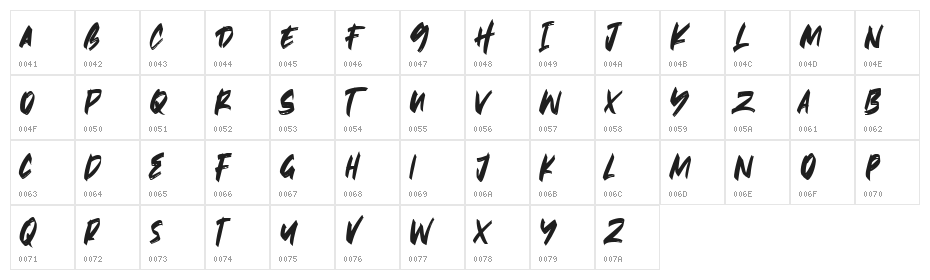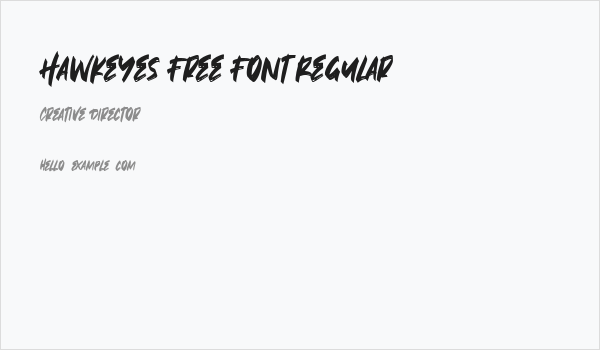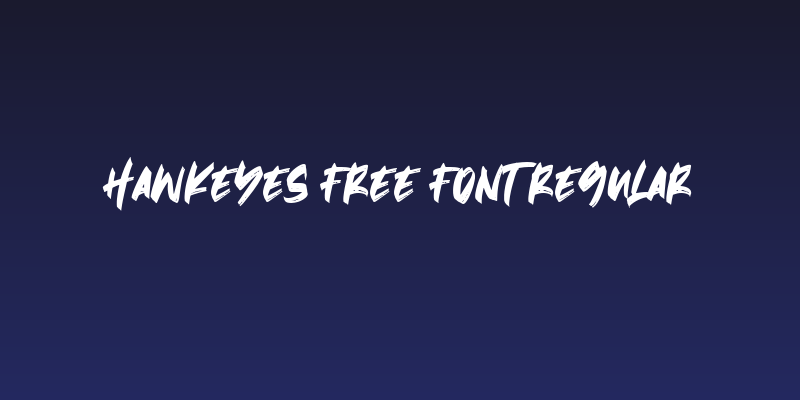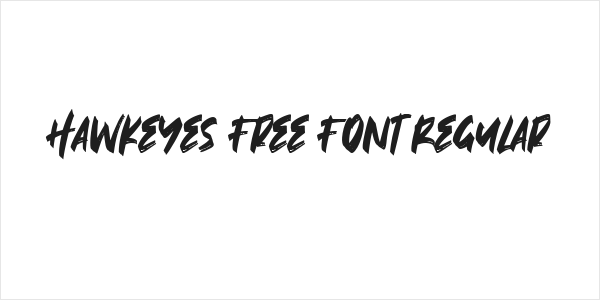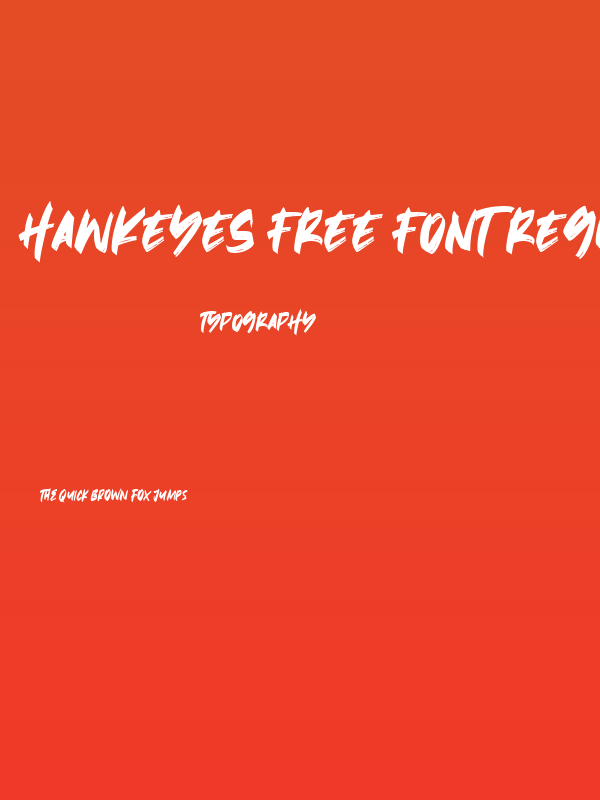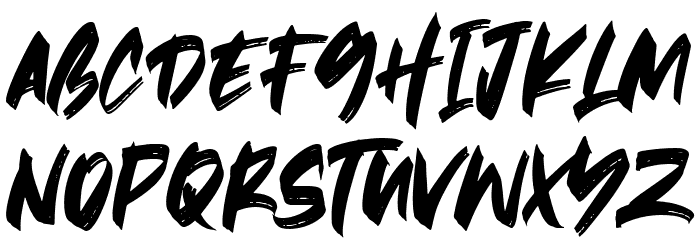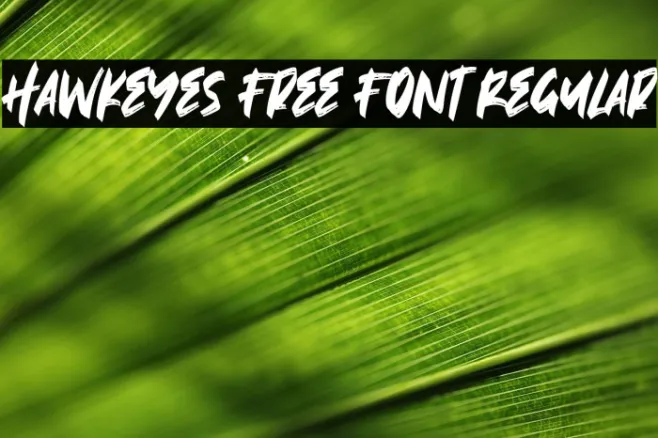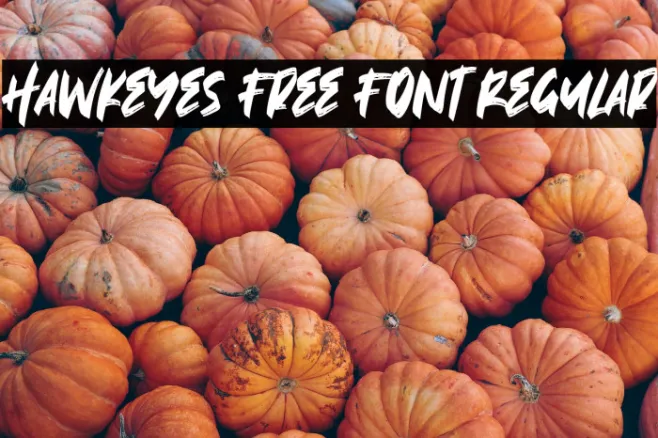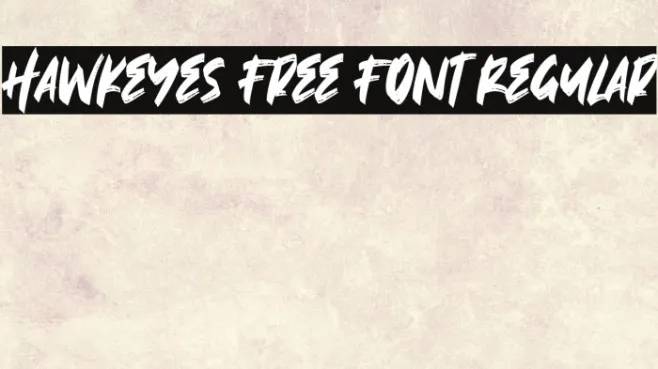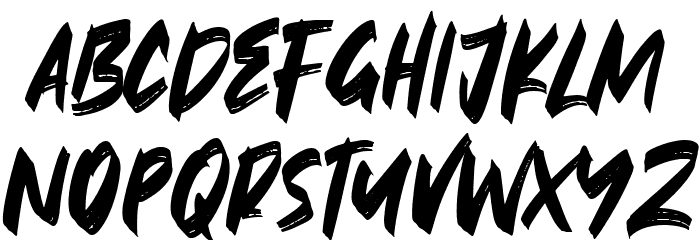
Hawkeyes Free Font Regular Font
| Caso de uso | Logos, Headlines, Posters |
| Proyectos propuestos | Ideal for branding, posters, album covers, and any project needing a bold, artistic statement. |